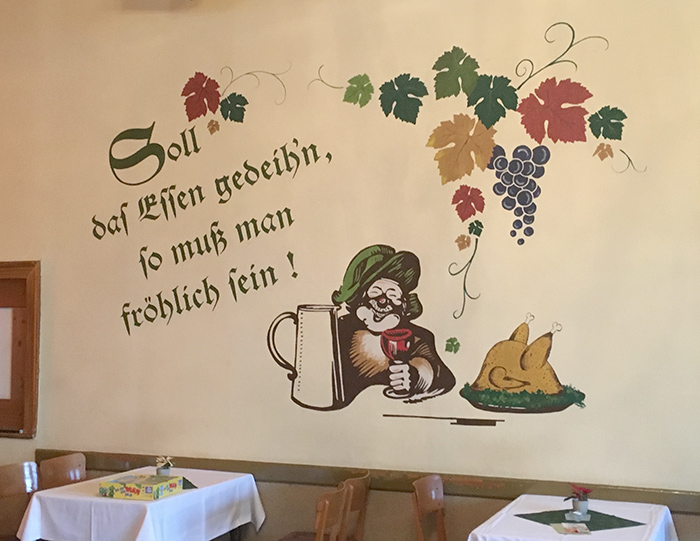
Langes s in heutigen Texten in gebrochener Schrift – notwendig, möglich oder unsinnig?
Das schlimmste ist ohnehin der (auch noch völlig unnötige) Stolperer im Versmaß. Insgesamt natürlich (Illustration, Orthographie, Typographie, Reimkunst) auch wieder stimmig.
Innerhalb der verschwindend seltenen heutigen Frakturtexte tendiert der Gebrauch des langen ſ meiner Meinung nach jedoch nicht gegen Null.
Ich vermute, wir sprechen da einfach von unterschiedlichen Anwendungen. Vielleicht kannst du ja mal Beispiele für die Anwendungen bringen, die du mit diesem Satz meinst.
Nein, wir sprechen nicht von unterschiedlichen Anwendungen, sondern wir drehen uns im Kreis. Du sagst immer wieder das Gleiche, und so mag ich halt meine Argumente nicht immer wieder neu formulieren, sondern antworte halt auch das Gleiche (vgl. Langes s in heutigen Texten in gebrochener Schrift – notwendig, möglich oder unsinnig? #132, Langes s in heutigen Texten in gebrochener Schrift – notwendig, möglich oder unsinnig? #179).
Ich persönlich würde es so zusammenfassen:
Wer in einem modernen Umfeld allein des grafischen Stils wegen eine Frakturschrift einsetzt, und hier der besseren allgemeinen Lesbarkeit wegen auch eine Schrift wählt, welche die Buchstaben k und x in der dem Antiqua-Skelett angepassten Form besitzt, kann, so er mag, auf das ſ verzichten, möchte er es aber verwenden, sollte ver sich an die alten Regeln auch halten, und ſ eben nie ans Wortende setzen.
Wer jedoch ein möglichst historisches, oder zumindest historisierendes Schriftbild anstrebt, und daher eine Frakturschrift verwendet, bei welcher das k wie ein t mit Rucksack, und das x wie ein r mit Schwanz wirkt, sollte auch das ſ nach den zuletzt gegen Ende des 20. Jahrhunderts im Duden genannten Regeln einsetzen. Hier kann dann auch an Stelle des ß die Kombination ſs - auch als Ligatur verwendet werden. sſ kann es aber nur an einer Wortfuge geben, z.B. Reichsſtraße
Ich fragte aber nicht nach Argumenten, sondern nach Beispielen. Die finde ich auch in den verlinkten Beiträgen nicht.
Jepp, mein Reden. Aber allein in den Raum zu stellen, dass etwas anderes als deine Variante zwei möglich oder gar »richtig« oder »empfehlenswert« wäre, löst dann halt immer wieder die gleichen Diskussionen aus.
Ich halte den im verlinkten Beitrag genannten Duden für das beste Beispiel. Eine repräsentative Auswertung von heutigen Frakturtexten ist mir nicht bekannt. Ich kenne nur rein impressionistische Sammlungen wie etwa unter langes s – Wikipedia, die natürlich nicht aussagekräftig sind. Unbestreitbar ist wohl einzig, dass die Fraktur heutzutage nur äußerst selten verwendet wird.
Mein persönlicher Eindruck (selbstverständlich nicht repräsentativ, sondern beruhend auf eigenen Beobachtungen von Schildern, Logos, Internetseiten usw. usw. sowie auf impressionistischen Sammlungen) ist der, dass die Fraktur oft als eine bloße Schriftart (font) verwendet wird, aber dass auch eine Verwendung als Schrift (script) mit eigenen typografischen Regeln vorkommt, vgl. langes s in heutigen Texten in gebrochener Schrift – notwendig, möglich oder unsinnig? #132.
die Fraktur [wird] oft als eine bloße Schriftart (font) verwendet, [aber auch als] als Schrift (script) mit eigenen typografischen Regeln
Klar, das ist offensichtlich. Der Gestalter der Plakate des Berliner Volksbühne sieht sich sicherlich im ersteren Camp, und die Leute vom BfdS sehen sich garantiert im zweiten.
Das bestätigt doch aber nur die These, dass es unsinnig ist, hier irgendwelche Regeln aufstellen zu wollen. Der Typograf entscheidet von Fall zu Fall. Fertig. :-?